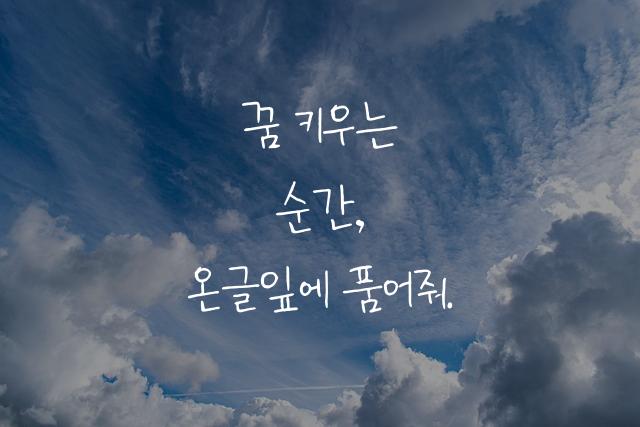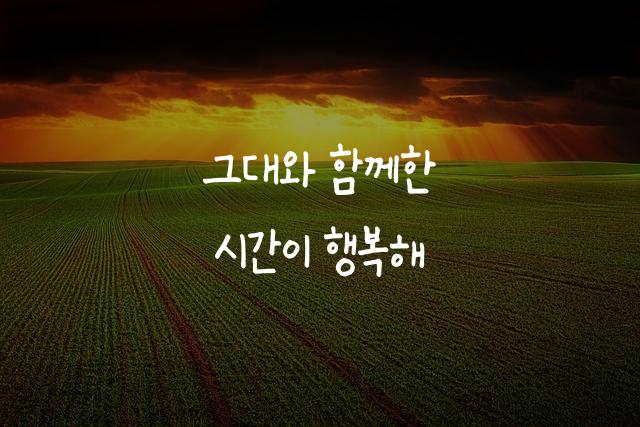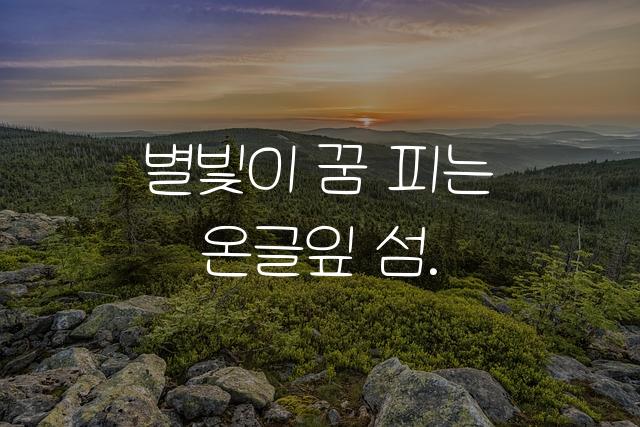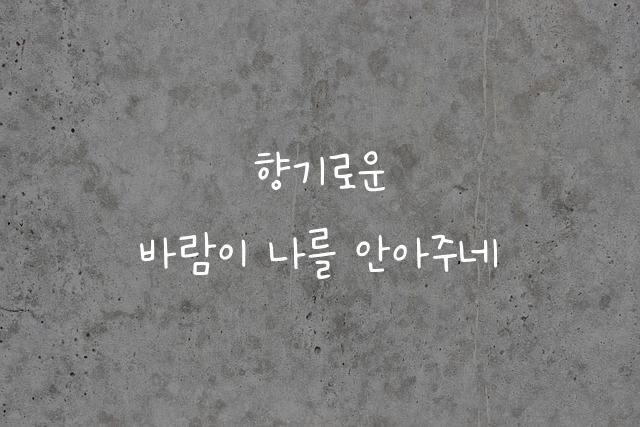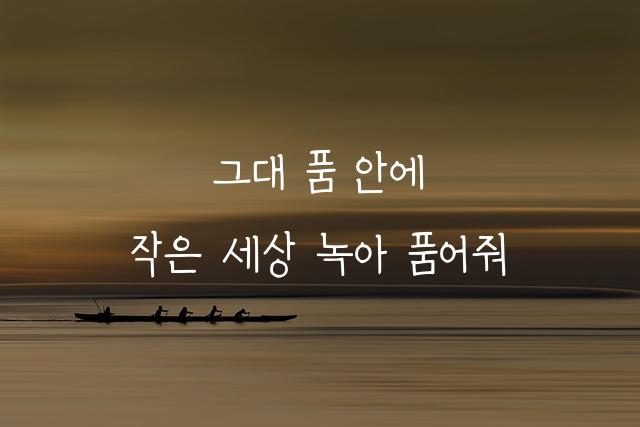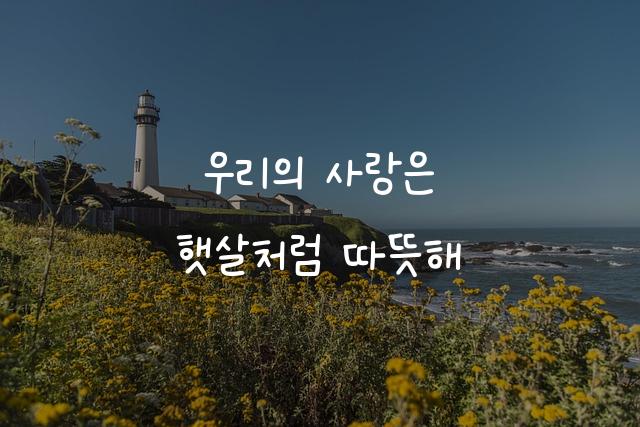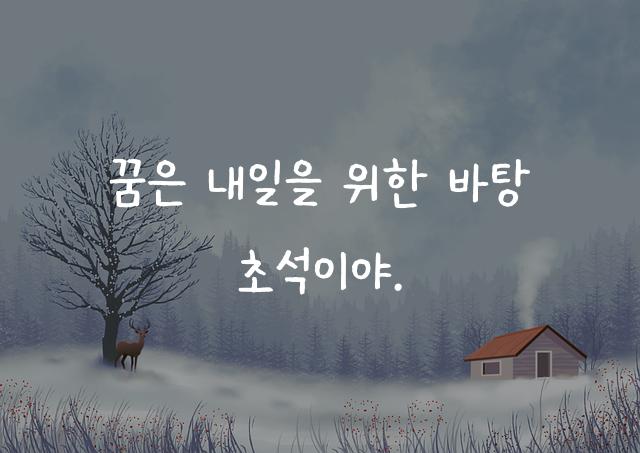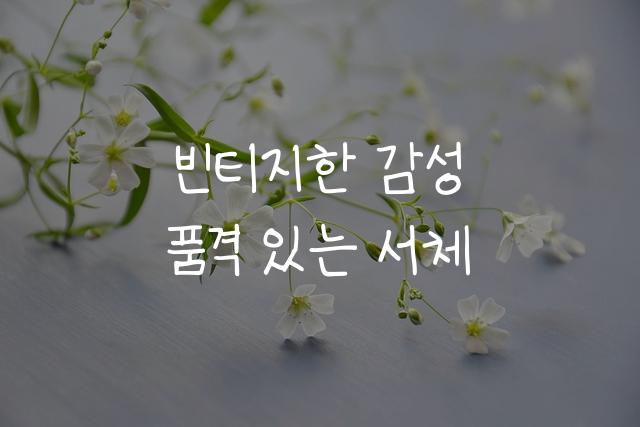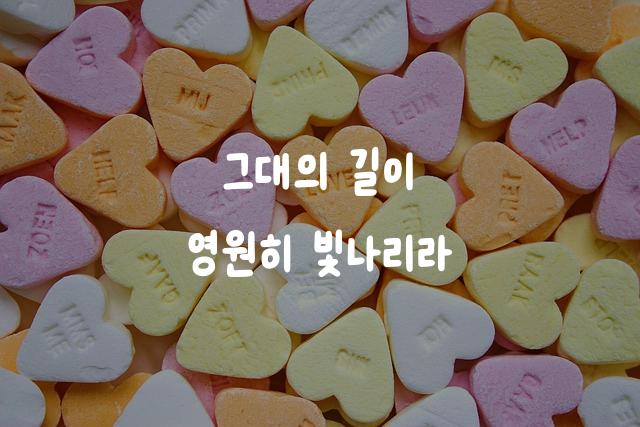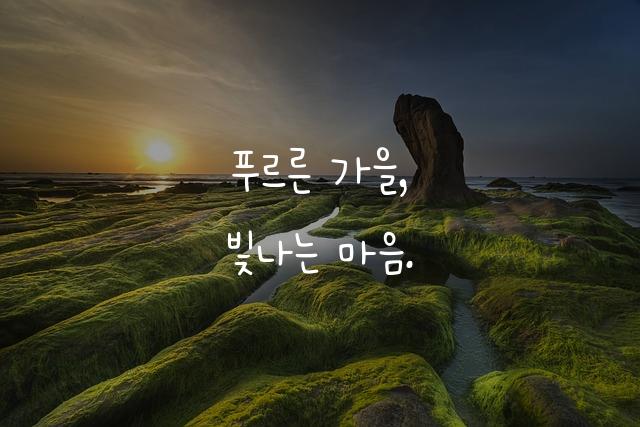
온글잎 위씨리스트
온글잎 위씨리스트는 캘리그라피와 펜을 사용하여 제작된 폰트로, 감성적이고 유동적인 라인이 특징입니다. 이 폰트는 따뜻한 감성을 전달하며, 글자마다의 개성이 돋보입니다.
따뜻하고 감성적이며, 개성 있는 필체
온글잎 위씨리스트은(는) 손글씨, 펜/붓터치, 감성적인 계열의 생김새를 가지고 있으며
초대장, 인사말 카드, 일기/편지 등에서 자주 활용되며, 효과적인 메시지 전달에 적합합니다.
이 폰트는 라이프스타일, 문화/예술, 이벤트/웨딩 분야에 잘 어울리며,
감성적인, 부드러운, 편안한 느낌을 담고 있는 것이 특징입니다.